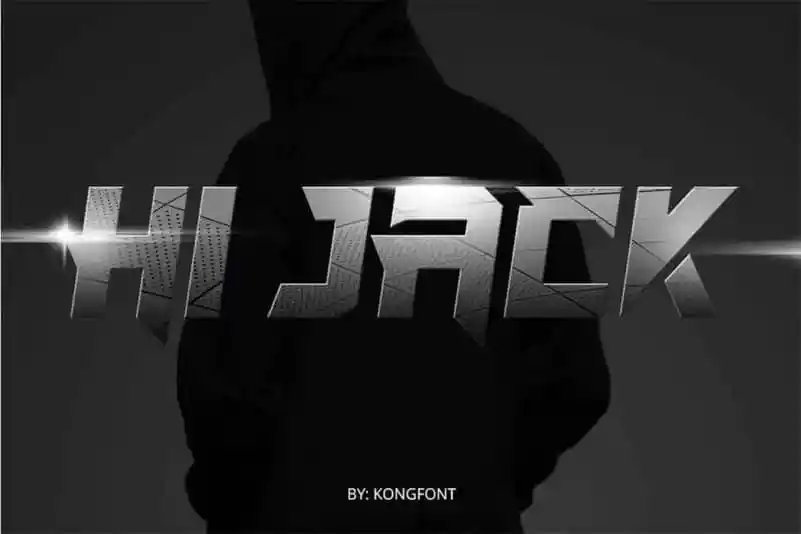
Hi Jack Display Font – Fonte Grátis
Hi Jack Display Font
A fonte “Hi Jack Display Font” é uma nova escolha para qualquer projeto que exija destaque e estilo. Esta fonte moderna e stylizada se destaca por suas formas quadradas e robustas, feitas especialmente para criar um visual chamativo e impactante. Com uma ampla gama de caracteres que inclui letras maiúsculas e minúsculas, números e um mínimo de pontuações, a “Hi Jack Display Font” oferece flexibilidade sem igual para criar ambientes de design únicos e memoráveis. Seja você criando materiais visuais ou aplicativos digitais, esta fonte trará sua marca em destaque no meio do concorrido mercado visual. Não perca tempo: explore o poder desta nova fonte que está aqui para deixar seu rastro na tela!